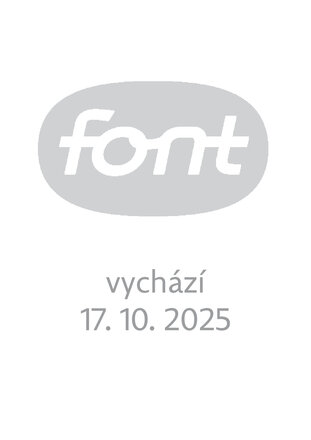
» Puvodni logo bylo citelnejsi, t...
» Dobrá práce, i když i já bych z...
» Logo na mě působí nedotaženým d...
» Musím říct, že se mi to moc nel...
» Poláci mají stejný, ...
Máte plnou pravdu....
» Soutěž skončila. Sláva vítězi, ...
» Hrabě X - no možná se bude divi...
» Dobrá práce, snad to Andy po vo...